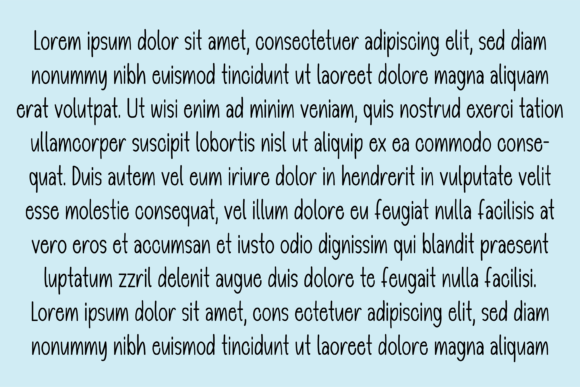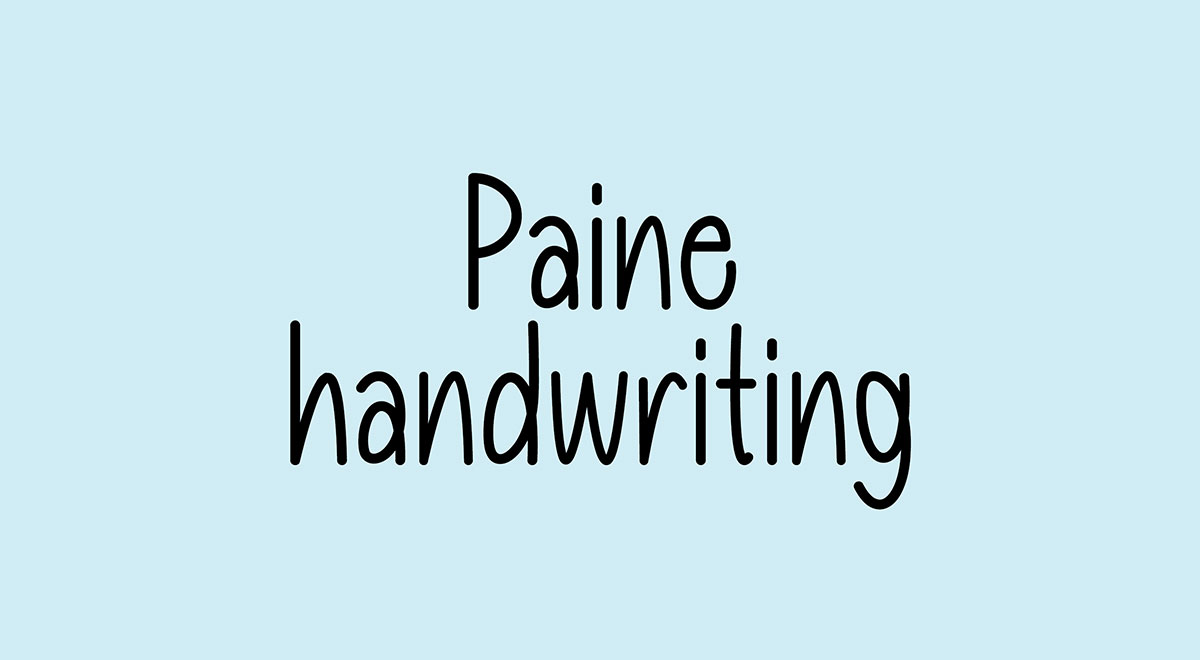
فونت Paine انگلیسی
| ⭐ توضیحات | Paine یک فونت دست نویس ساده و دوستانه است. عجیب و غریب و کمی عجیب و غریب، این فونت طرح های شما را درخشان می کند. آن را با اطمینان به پروژه های خود اضافه کنید و از نتایج لذت خواهید برد. این فونت برای آرم ها، دعوت نامه های عروسی، نقل قول ها، تبلیغات، چاپ، مجلات و موارد دیگر عالی است! |